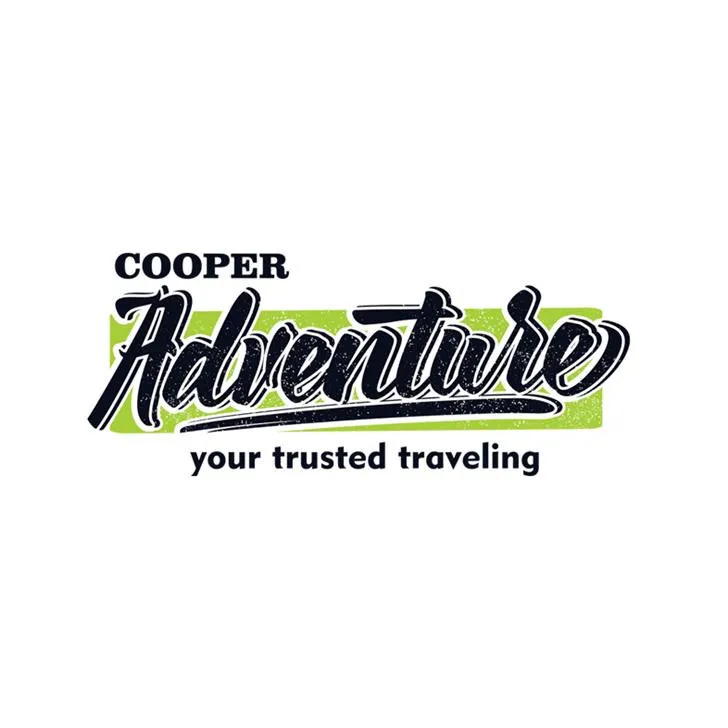
Vizels font – Download Grátis
A Vizels Font é uma elegante fonte de estilo oriental projetada especialmente para a prática do xíngxiào, ou escrita chinesa. Sua graça e fluididade são perfeitamente adaptadas para gráficos que buscam transmitir um toque de riqueza cultural no design. Foi desenvolvida pelo designer Hamilton, oferecendo uma textura única capaz de dar vida à sua ideia através de linhas suaves e traços delicados. Este é o ideal para aqueles buscando incorporar elementos chineses em projetos gráficos que valorizam a escrita por dentro. Para um uso comercial, visite nosso site http://vmffont.bigcartel.com/products ou explore nossa seção de licenças através do Creative Market. Para quem está procurando um recurso de qualidade para seu trabalho de design, a Vizels Font é uma excelente escolha, proporcionando aos artistas e designers a oportunidade de adicionar profundidade e personalização ao seu trabalho. Este não apenas oferece características únicas que vão além da simples leitura legível, mas também traz à vida a arte e a história do xíngxiào através das letras. Com ela, você pode explorar novos territórios gráficos sem perder o encanto tradicional.